고딕체 명조체 차이, 용도로 바로 고르는 법
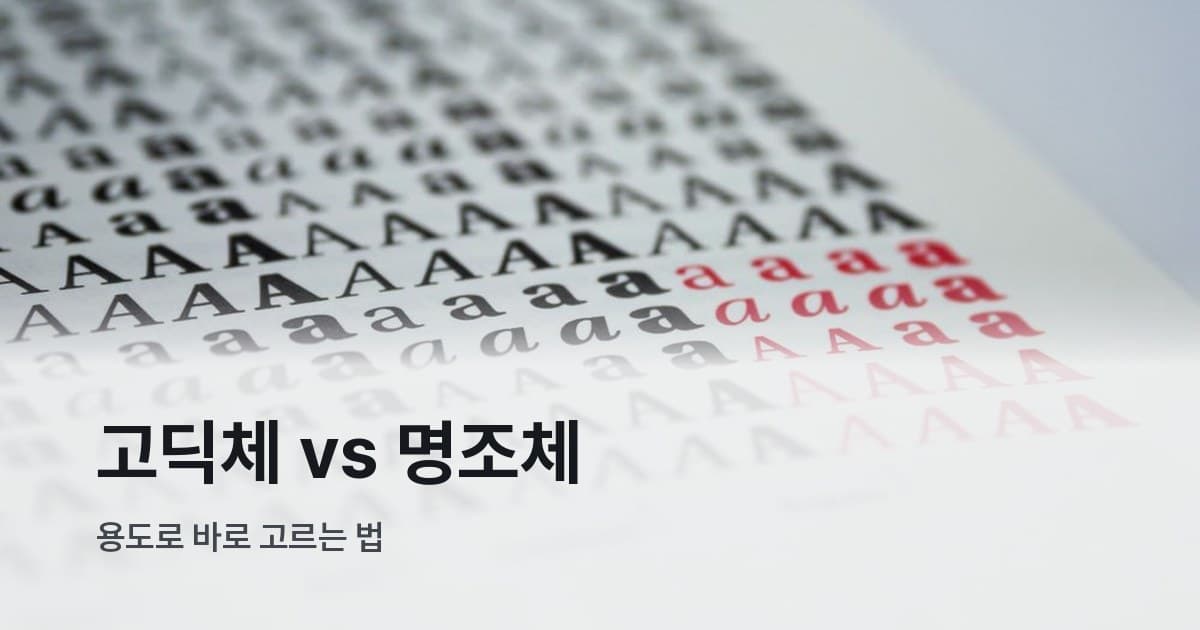
지금 만드는 게 웹 페이지인가요, 인쇄물인가요, 아니면 PPT인가요? 이 질문 하나면 고딕/명조 판단의 거의 대부분은 끝납니다. 개념을 다 알 필요도 없어요 — 내 상황에서 어느 쪽 길로 가면 되는지, 그 분기점부터 짚어볼게요.
고딕·명조, 같은 말인데 용어가 두 벌인 이유
한글 타이포그래피와 서양 타이포그래피는 용어 체계가 달리 발전했는데, 사실상 가리키는 건 같아요.
- 고딕체 = 산세리프(Sans-serif): 획 끝에 삐침이 없고 굵기가 일정하게 이어지는 형태예요. 'Sans'는 프랑스어로 '없다'는 뜻.
- 명조체 = 세리프(Serif): 획 끝에 작은 돌기가 붙어 있고, 가로·세로 획의 굵기 차이가 있어요. 붓글씨에서 비롯된 형태죠.
국내 디자인 현장에서는 고딕/명조로 부르고, 영문 폰트나 국제 문서에선 산세리프/세리프를 씁니다. 손글씨체(스크립트)와 장식체(디스플레이체)도 있는데, 이 둘은 제목이나 포인트용으로만 쓰고 장문 본문에는 거의 쓰지 않아요. 이 글은 고딕/명조 두 계열을 집중해서 다룹니다.
"화면엔 고딕, 인쇄엔 명조"가 무너지는 지점
오래된 타이포그래피 상식이 있어요. "세리프는 인쇄에 좋고, 산세리프는 화면에 좋다"는 것. 이 말은 저해상도 화면(72~96 PPI)에서 세리프 돌기가 픽셀로 뭉개져 읽기 어려워진다는 관찰에서 나왔거든요.
그런데 지금은 상황이 달라졌습니다. 스마트폰과 노트북 화면 해상도가 200~400 PPI(레티나·QHD)까지 올라가면서, 세리프 돌기도 선명하게 표시할 수 있어요. Richardson(2022, Springer Nature) 연구는 현대 디스플레이에서 세리프와 산세리프의 읽기 속도·이해도 차이가 통계적으로 유의미하지 않다고 결론 내렸습니다.
그래서 지금 기준으로 두 계열의 가독성 차이는 계열 자체보다 폰트 품질, 크기, 자간, 행간에 더 크게 좌우됩니다. 계열이 읽힘을 결정하는 게 아니라 분위기와 관습적 쓰임을 결정하는 거예요. 이 사실이 중요한 이유는 이어지는 판단 흐름에서 드러납니다.
내 작업에 어느 계열이 맞는지 갈라보기
막막할 때는 순서대로 따라오면 됩니다. 첫 번째 갈림길은 매체예요.
매체가 화면(웹·앱·PPT·영상)인가
화면이라면 → 고딕/산세리프가 기본값입니다.
이유는 두 가지예요. 첫째, 한글 웹폰트 생태계 자체가 고딕 중심으로 발전해서 본고딕·나눔고딕·Pretendard처럼 렌더링이 검증된 폰트가 고딕 계열에 몰려 있어요. 둘째, 프로젝터 환경(PPT)이나 짧은 노출 시간(영상 자막)에서는 굵고 단순한 형태가 훨씬 빠르게 읽힙니다. 화면이라는 조건이 들어오는 순간 계열 고민은 사실상 끝나는 거예요.
화면인데도 명조를 써야 할 때가 있긴 합니다 — 브랜딩 목적의 제목 한 줄이나 워드마크처럼, 분위기 전달이 목적이고 장문 가독성이 필요 없는 경우요. 이 경우는 아래 분위기 분기에서 다시 갈립니다.
매체가 인쇄물이라면 — 분량이 기준이 된다
인쇄물이라면 두 번째 갈림길은 텍스트 분량입니다.
500자 미만 짧은 텍스트(제목·캐치카피·패키지 표기)라면 → 계열 제약이 거의 없어요. 분위기 판단으로 넘어갑니다.
500자 이상 이어지는 장문 본문이라면 → 명조/세리프 검토로 갑니다. 고해상도 인쇄에서 세리프 돌기가 시선의 흐름을 가로 방향으로 유도해 줘서, 긴 문장을 읽을 때 눈이 덜 피로해지는 효과가 있어요. 단, "명조가 항상 낫다"는 게 아니라 "인쇄 장문이라면 명조를 진지하게 검토할 이유가 생긴다"는 의미예요.
인쇄 장문인데 고딕을 유지하고 싶다면 — KoPub돋움처럼 출판·eBook 최적화 고딕을 쓰면 됩니다. 이 경우엔 행간과 자간을 명조 기준으로 넉넉히 잡는 게 중요해요.
분위기가 마지막 갈림길
매체·분량으로도 결론이 안 날 때(예: 인쇄 단문, 로고, 브랜드 워드마크), 분위기로 갑니다.
격식·신뢰·권위가 필요한 맥락(법률 문서, 학술 보고서, 고급 브랜드 패키지)이면 → 명조/세리프. 현대적·깔끔·전문적이거나 따뜻·친근·감성적인 분위기가 필요하면 → 고딕/산세리프. 강렬한 임팩트가 필요한 포스터·이벤트 배너는 → 굵은 고딕(헤비 웨이트)으로 가면 대부분 해결됩니다.
전통·클래식·고풍스러운 분위기라면 명조/세리프가 잘 맞아요. 전통 식품 브랜드, 문화재 관련, 한옥 브랜드가 여기 해당합니다.
결국 세 갈림길을 지나면 한 곳으로 모입니다. "인쇄 장문 + 격식·신뢰" 조합에서만 명조/세리프가 두드러지게 권장되고, 나머지 거의 모든 조합에선 고딕이 기본값으로 작동해요. 판단이 여전히 애매하다면 고딕으로 시작하는 게 실무적으로 가장 안전합니다.
분기를 잘못 타는 흔한 순간들 ✍️
판단 흐름을 알아도 실제로 자주 틀리는 지점이 있어요.
"화면이니까 고딕"이라고 했다가 명조로 돌아오는 경우 — 웹 브랜딩 작업에서 제목 폰트만큼은 명조를 써서 격조를 주고 싶은데, 본문 고딕과 섞이면 이상하다고 느끼는 경우입니다. 이건 실수가 아니에요 — 제목과 본문의 계열이 달라도 역할이 분리되면 충분히 작동합니다. 섞는 게 문제가 아니라 역할 없이 섞는 것이 문제예요.
PPT에 명조를 본문 폰트로 쓰는 경우 — 프로젝터 해상도와 조명 환경에서 세리프 돌기가 뭉개져 보일 수 있어요. 포인트·제목에 명조를 쓰는 건 무방하지만, 본문은 고딕이 안전합니다.
계열을 바꾸기 전에 굵기부터 바꿔봤는가 — 솔직히 계열보다 굵기 대비가 레이아웃에서 더 강한 역할을 할 때가 많아요. 같은 고딕 계열에서 제목은 Bold/ExtraBold, 본문은 Regular/Light를 쓰는 게 다른 계열을 섞는 것보다 훨씬 정리된 느낌이 나거든요. 계열이 달라 보이는 문제의 원인이 사실은 굵기 차이 부재인 경우가 꽤 많습니다.
명조를 웹 본문 전체에 쓰는 경우 — 기술적으로 불가능하진 않지만, 한글 명조 웹폰트는 파일 크기가 크고 렌더링 품질 편차가 있어요. 화면 크기·해상도가 제각각인 환경에서는 고딕이 훨씬 일관된 결과를 보여줍니다.
계열별로 바로 쓸 수 있는 한글 폰트
고딕/산세리프 계열
| 폰트명 | 제작 | 특징 | 주요 용도 |
|---|---|---|---|
| 본고딕 (Noto Sans KR) | Google·Adobe 공동 | 7가지 굵기, 한중일 통합 지원, OFL | 웹·앱 본문, UI |
| 나눔고딕 | 네이버 | 본문용 최적화, OFL | 웹 본문, 문서 |
| KoPub돋움 | 한국출판인회의 | 출판·eBook 본문용, 공공누리 1유형 | 인쇄·전자책 |
| Pretendard | 길형진(orioncactus) | 시스템 폰트 대체, 가변폰트 지원 | 웹·앱 UI |
명조/세리프 계열
| 폰트명 | 제작 | 특징 | 주요 용도 |
|---|---|---|---|
| 본명조 (Noto Serif KR) | Google·Adobe 공동 | 전통미 + 현대 가독성, OFL | 인쇄 본문, 브랜드 |
| 나눔명조 | 네이버 | 직선적·날카로운 명조, OFL | 인쇄·편집 디자인 |
| KoPub바탕 | 한국출판인회의 | eBook·출판 최적화, 공공누리 1유형 | 전자책·인쇄 장문 |